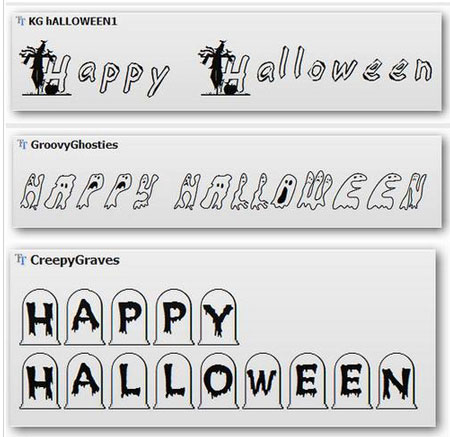
Halloween Fonts với font chữ chữ với rất nhiều kiểu chữ viết độc đáo mang tính nghệ thuật vô cùng đẹp mắt. Bộ phông chữ Halloween Fonts sẽ là lựa chọn tuyệt vời dành cho những ai đang muốn thiết kế những thứ liên quan đến lễ hội hóa trang, chắc chắc Halloween Fonts sẽ góp phần không nhỏ cho thành công của ngày lễ tuyệt vời này.
Halloween Fonts được vẽ tay mang phong cách Halloween được lấy cảm hứng từ những bộ xương cổ đại và những con tàu cướp biển ma quái. Nó có thiết kế vui nhộn, nhẹ nhàng không kém phần rùng rợn vì vậy khá phù hợp cho các thiết kế liên quan đến lễ hội vui nhộn này.
Lễ hội Halloween là một trong những lễ hội lớn nhất trong năm của phương Tây diễn ra vào ngày 31 tháng 10 hàng năm.. Đây là dịch để mọi người trang hoàng nhà cửa, họ lên chủ đề và cùng nhau thực hiện với gia đình hay những người bạn. Thông qua bộ font chữ Halloween này chúng ta sẽ thỏa sức sáng tạo ra những món quà tặng hay tác phẩm mang đậm không khí vui nhộn nhưng cũng hết sức đáng sợ theo đúng tiêu chuẩn của lễ hội.
Vào ngày này, giới trẻ, nhất là học sinh, sinh viên thường tổ chức những buổi lễ độc đáo, hóa trang và trang hoàng không gian theo phong cách “rùng rợn” và đáng sợ. Với bộ font chữ mang chủ đề Halloween dưới đây, bạn có thể sử dụng để chèn vào những bức ảnh, những tấm card, vv để làm độc đáo hơn cho ngày lễ hội.